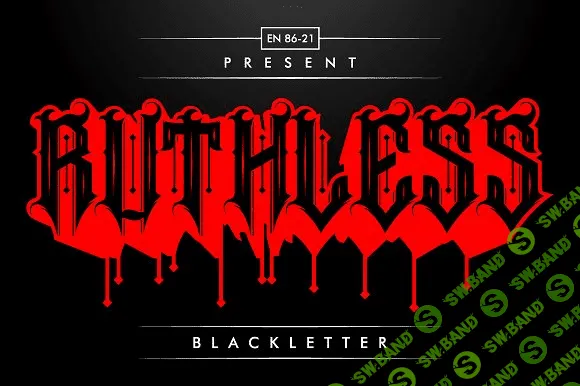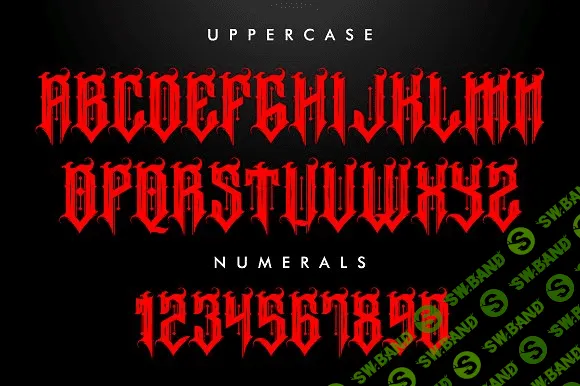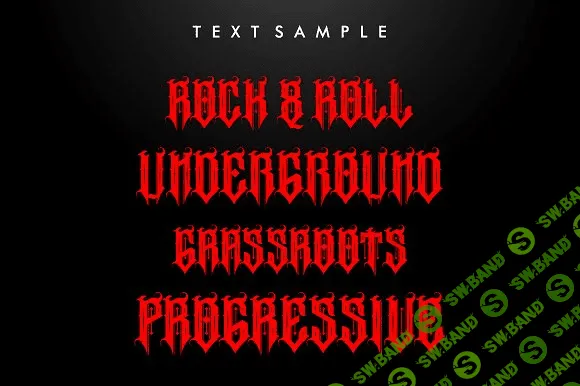
Название: Ruthless Typeface
Описание:
EN 86-21 представляет Ruthless, вдохновленный татуировкой и логотипом группы. Продукт содержит: Ruttially.TTF (формат TTF). В комплект поставки входят: прописные буквы, строчные, цифры, знаки препинания, спасибо за интересный продукт
Название: Ruthless Typeface
Описание:
EN 86-21 представляет Ruthless, вдохновленный татуировкой и логотипом группы. Продукт содержит: Ruttially.TTF (формат TTF). В комплект поставки входят: прописные буквы, строчные, цифры, знаки препинания, спасибо за интересный продукт